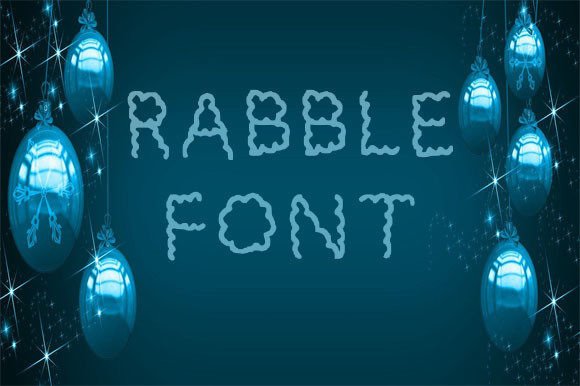
Rabble
Ulasan Font Rabble – Avaliação Completa, Prós e Contras
Rabble – Uma Fonte Manuscrita Divertida e Diferente
Se você procura uma tipografia que traga um toque descontraído e único aos seus projetos, a Rabble pode ser a solução perfeita. Criada com estilo hand‑written, ela combina traços irregulares e um charme “feito à mão”, ideal para quem quer se destacar sem perder a legibilidade.
- Estilo Handwritten: Linhas soltas e variações de espessura que simulam uma escrita real.
- Versatilidade: Funciona bem em logotipos, convites, capas de livros, posts de redes sociais e até em branding de marcas jovens.
Prós e Contras
- Pró: Design exclusivo que adiciona personalidade instantânea.
- Pró: Excelente legibilidade mesmo em tamanhos menores.
- Pró: Fácil de combinar com fontes sans‑serif para contrastes modernos.
- Contra: Pode não ser adequada para textos longos ou documentos formais.
- Contra: Algumas variações de peso são limitadas; se precisar de negrito intenso, será necessário criar manualmente.
Quando Usar a Rabble?
Rabble brilha em situações que pedem criatividade e humanização da comunicação visual. Considere-a para:
- Cartões de visita de startups criativas.
- Convites de festas, casamentos e eventos temáticos.
- Headers de blogs de lifestyle, moda ou design.
- Ilustrações de capas de livros infantis.
- Postagens de redes sociais que precisam de destaque visual.
Em resumo, a fonte Rabble entrega exatamente o que promete: um visual divertido, descontraído e pronto para transformar qualquer projeto em algo memorável. Se você quer dar um toque de personalidade sem sacrificar a clareza, adicione Rabble ao seu arsenal tipográfico e experimente resultados que realmente encantam.